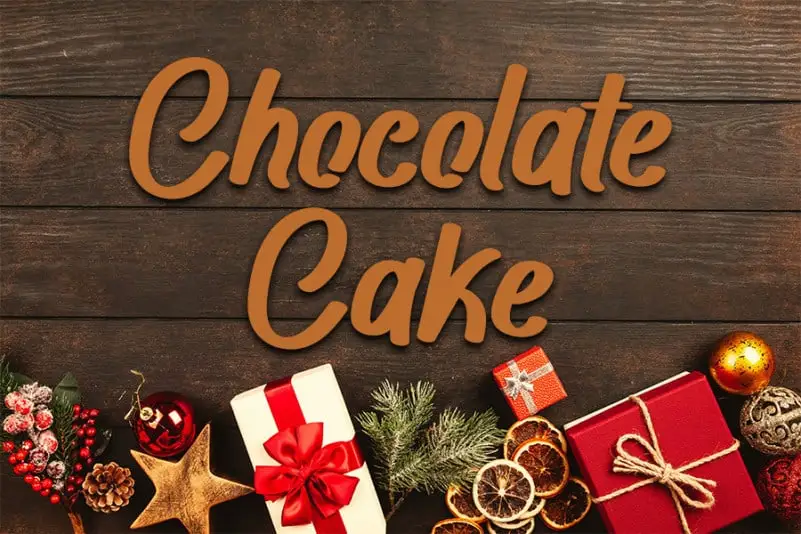
A Chocolate Cake Brush Font é uma opção elegante para quem busca um estilo casual e contemporâneo. Essa fonte foi projetada com influências do script manuscrito, mantendo sua classe clássica ao mesmo tempo que parece atual e fresco. Suas formas fluidas e personalizadas tornam-a perfeita para uma infinidade de ideias crafty, sejam elas para estilizar assentos ou títulos, até enfeites de papelaria. Para quem procura um complemento versátil para diversos ambientes gráficos, essa fonte é certamente o item a ser adicionado ao seu estoque. Ela será especialmente apreciada por designers e criativos que buscam uma fonte que transmite elegância ao mesmo tempo em que traz uma sensação de modernidade e frescura.